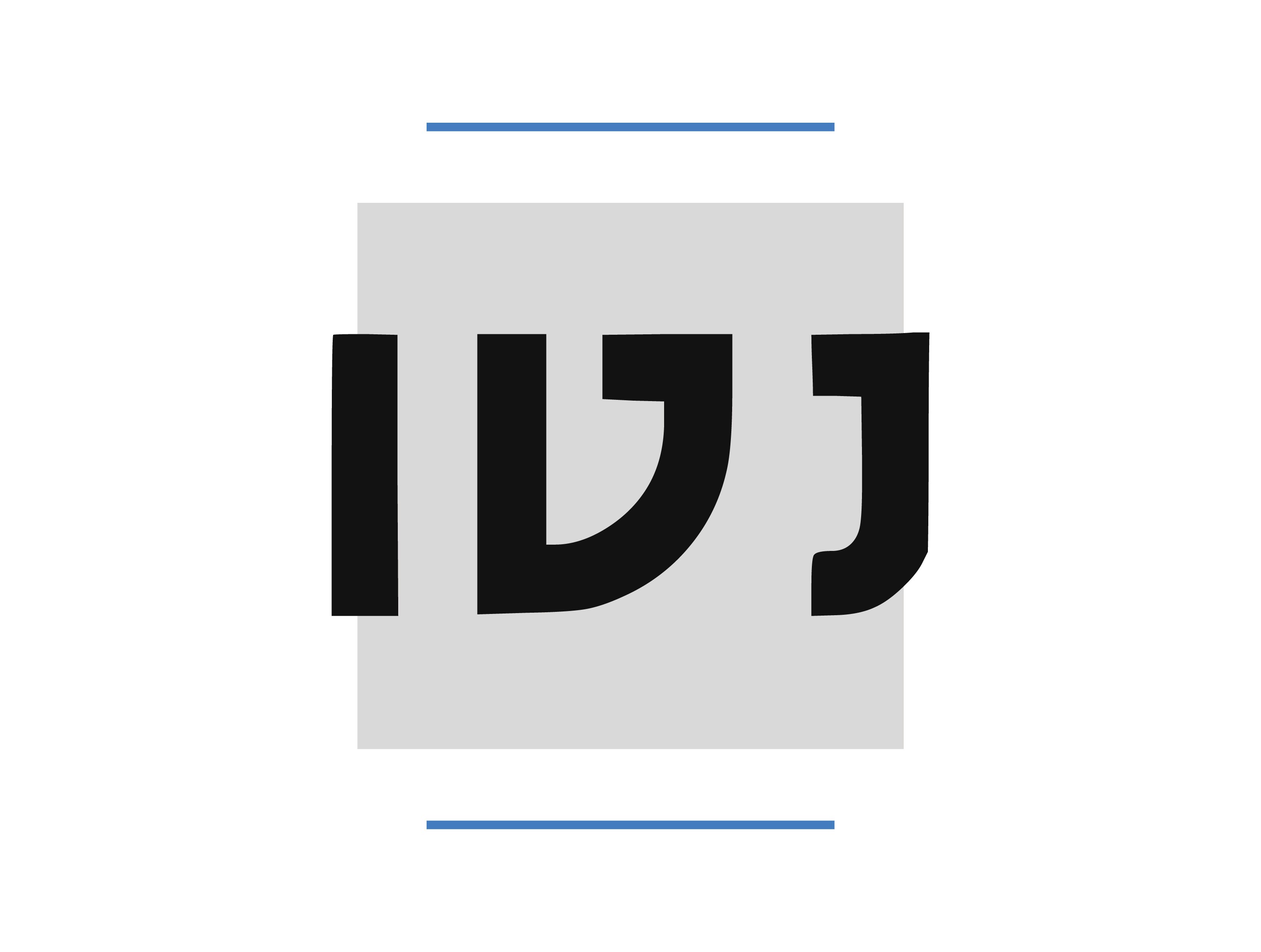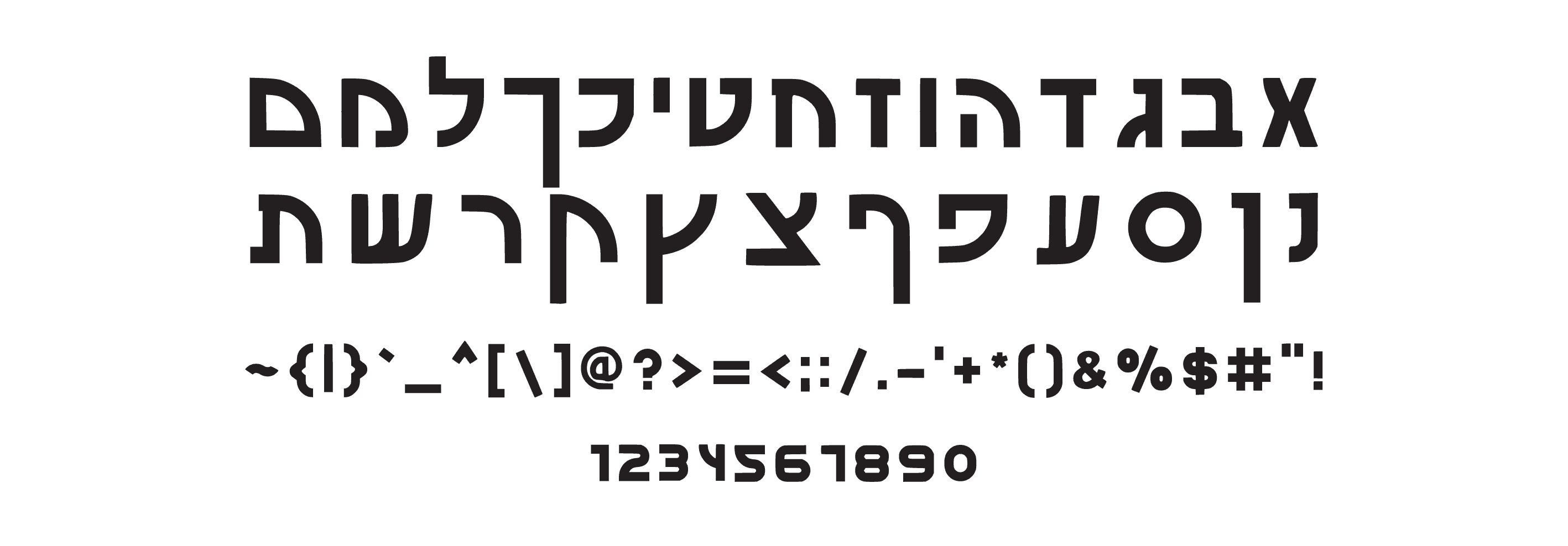
פונט נטו
פונט עברי מינימליסטי, גאומטרי ופונקציונלי, אידיאלי לממשקים, כותרות ואתרים.
נטו — פשוט, מדויק, נכון
לפעמים, כל מה שצריך הוא פונט שלא מתבלבל.
נטו הוא פונט עברי סנס-סריפי, מינימליסטי וישיר, שמתמקד בדיוק ובקריאות, בלי משחקים מיותרים.
עם קווים גאומטריים חדים ומראה נקי ומודרני, הוא משתלב בצורה מושלמת בממשקים, אתרים, אפליקציות, עיצובים טכנולוגיים וטקסטים שדורשים סדר ובהירות.
האותיות של נטו בנויות כך שיישארו ברורות בכל גודל, מבלי לאבד מהאופי האלגנטי והמדויק שלהן.
איפה הוא מרגיש בבית?
🖥️ ממשקי משתמש (UI/UX)
📰 כותרות ותוכן במגזינים מודרניים
🏷️ עיצובי מיתוג וטכנולוגיה
📊 גרפיקות ומצגות עסקיות
למי הוא מתאים?
למעצבים שמעדיפים פשטות, פונקציונליות ומודרניות — בלי לוותר על נראות נקייה ומדויקת.